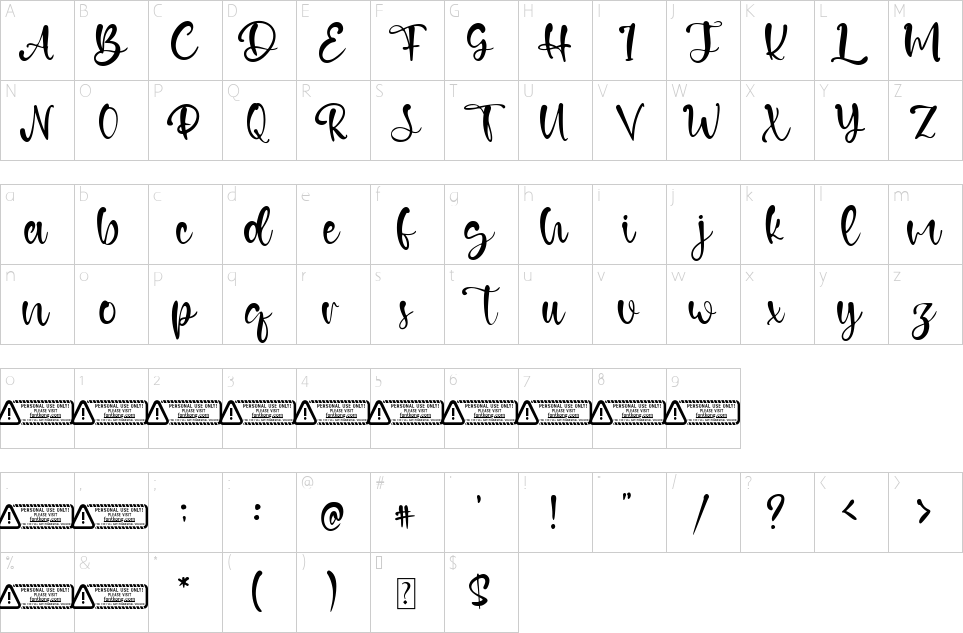
Aqui está uma descrição em português para a página de download da fonte ‘Dennison Font | 1001 Free Fonts’ seguindo as instruções fornecidas: A Fonte Dennison está disponível em formato para Windows e Mac, e foi criada pela Font Kong. Com design simples e elegante, a Dennison se destaca como uma opção popular para designers e profissionais de gráfica em busca de uma fonte grata de alta qualidade para seus projetos. Com uma interface intuitiva e facilidade de uso, a Dennison oferece um leque de opções únicas que podem ser utilizadas para criar textos atraentes em qualquer formato de documento, seja ele um website, design de mídia social ou até mesmo em um projeto de gráfica. Com mais de 1.782 downloads, a Dennison é uma fonte extremamente popular e uma ótima escolha para quem busca estilizar sua produção visual de forma elegante e profissional.